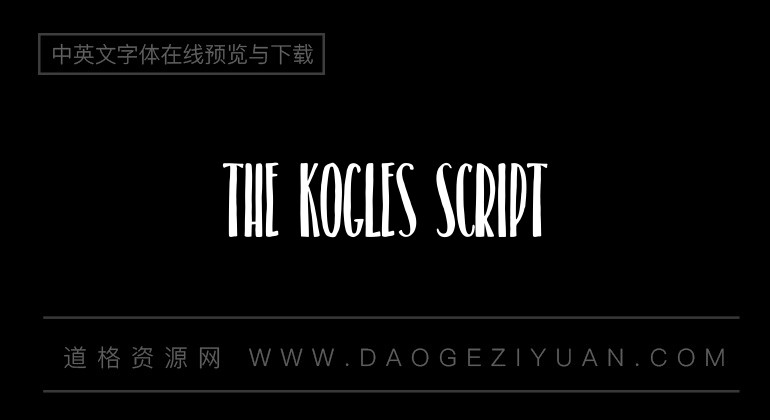
The Kogles Script
? The Kogles Script字体是一款由Kogles设计的手写字体,具有温暖、舒适、活泼的特点,具有细腻、优雅的曲线,可以为您的项目提供独特的视觉效果。它的字形具有良好的可读性,可以用于海报、标识、标题、卡片、礼品和其他设计,为您的项目带来极具吸引力的外观。
The Kogles Script是一款非常不错的手写艺术字体,具有很好的视觉感,适合于文化类的宣传设计、商业类品牌的广告和产品包装设计以及个性化文字排版等较多场景。